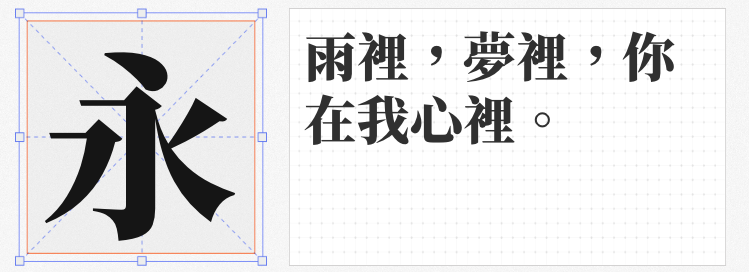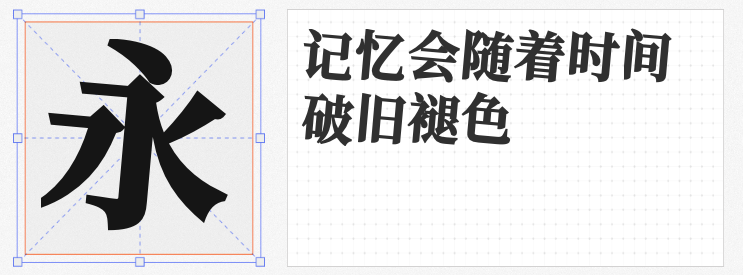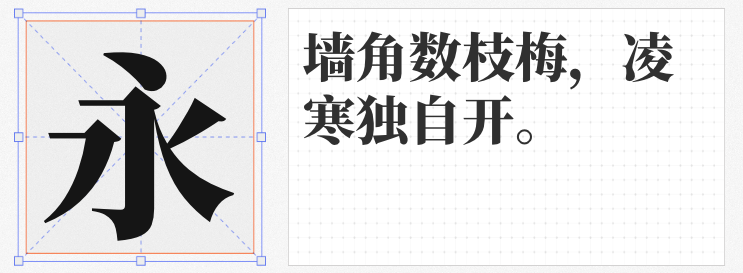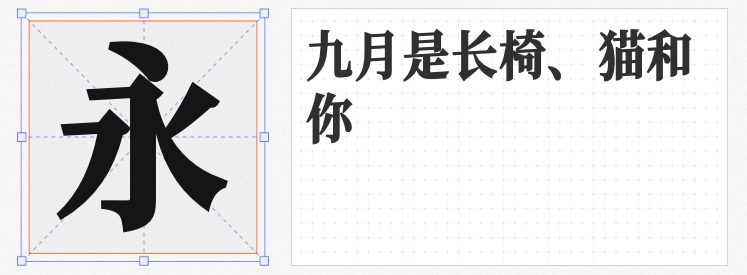
在平面设计与品牌视觉中,超粗宋体以其刚劲有力的笔画和鲜明的结构感,成为标题、海报、LOGO等场景的“视觉锚点”。本文精选四款免费商用超粗宋体字体,均基于开源字体改造或官方授权发布,兼顾设计质感与法律合规性,助力设计师高效输出高辨识度作品。
作为Adobe与Google联合发布的泛CJK字体,思源宋体 CN Heavy以SIL Open Font License 1.1协议开源。其笔画横平竖直、转折利落,衬线设计强化了视觉重量感,适合用于书籍封面、文化类海报等需要传递权威感的场景。
基于新愚公和谐宋改造的猫啃网文明宋-H,通过微调长宽比解决了原版字形“头重脚轻”的问题,视觉更协调。其超粗字重强化了宋体的装饰性,适合电商促销、短视频封面等需要快速抓取注意力的场景。
由思源SC宋体脚本改造的新愚公自由宋-H,通过算法切割笔画层次,营造出线条分明的机械感。其超粗字重进一步放大了这种张力,适合科技、运动类品牌的视觉系统设计。
基于可变版思源宋体插值生成的梦源宋体 TW W27,通过线性插值算法提取27个中间字重,其中W27为最粗版本。其笔画粗细过渡自然,适合需要多层级标题的杂志排版或品牌VI手册。
无论是追求权威感、机械风还是精细调控,这四款超粗宋体都能为设计注入强劲的视觉能量,让文字从“阅读载体”升级为“设计语言”。